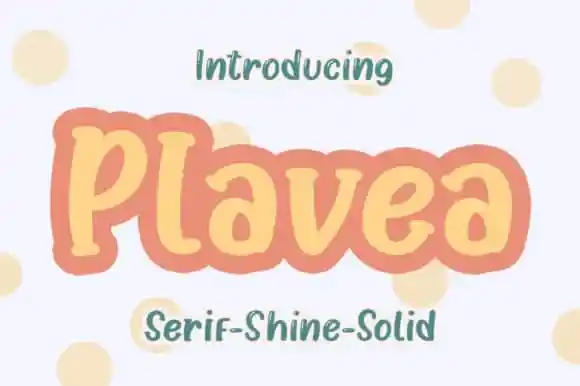
Introduzimos a Plavea Display Font, uma tipografia display que transmite leveza e casualidade. Essa tipografia é perfeitamente adequada para headlines, títulos e logomarcas, especialmente projetos de design focados no tema divertido ou descontraído. A Plavea Display Font foi criada por agamous. Ela é uma fonte display alegre e acolhedora, ideal para dar vida aos seus ideais mais criativos. Seja você um designer que busca dar destaque a suas mensagens de forma vibrante, seja um criador de logomarcas procurando por uma identidade única e descontraída ou um artista buscando um estilo animado e divertido em seu próximo projeto, a Plavea Display Font pode ser sua escolha perfeita.